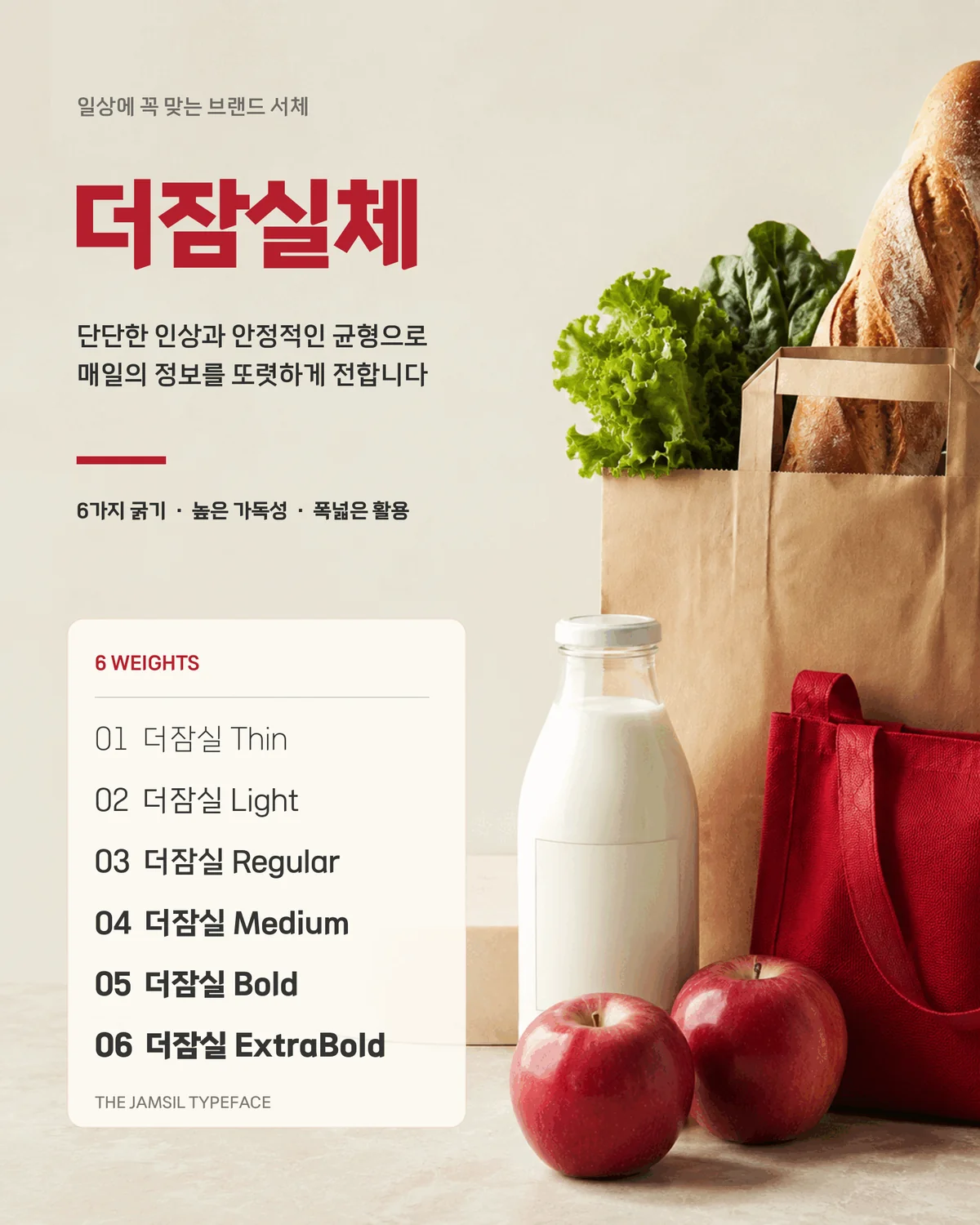
더잠실체 — 롯데쇼핑에서 배포하는 무료 폰트입니다. 누에고치와 명주실의 형태를 담아 단단함과 부드러움을 함께 표현한 고딕체
롯데쇼핑 롯데마트사업부가 폰트릭스와 함께 만들어 2023년 2월에 공개한 서체입니다. 총괄은 폰트릭스의 박용락 디자이너가 맡았고 개발에 열 달 남짓 걸렸습니다. 롯데마트의 신입 디자이너 열 명 남짓이 의견을 내 트렌드와 범용성을 검토했다는 점도 알려져 있습니다.
이름을 오해하기 쉬운데 롯데월드타워와는 관계가 없습니다. 잠실은 롯데의 출발점인 지역 이름이고, 한자로는 蠶室, 곧 누에를 치는 방이라는 뜻입니다. 모티브가 여기서 나옵니다. 제작사 설명 그대로, 누에가 뽕잎을 먹기 위해 머리를 드는 모습부터 누에고치를 만드는 과정, 마지막으로 누에고치에서 실을 뽑아내는 모습까지를 현대적으로 해석해 서체에 적용했습니다. 폰트릭스는 누에고치를 닮은 ㅇ꼴과 명주실의 생동감을 표현한 힘 있는 각을 특징으로 꼽습니다.
굵기는 여섯 가지로 이 목록에서 가장 촘촘한 축이고 베트남어와 인도네시아어까지 지원합니다. 라이선스에 한 가지 강한 조항이 있습니다. 인쇄와 출판, 영상, 웹, 모바일에는 자유롭게 쓸 수 있지만 서체를 수정하거나 다른 포맷으로 변형하는 것은 엄격하게 금지됩니다.
더잠실체는 롯데마트 브랜드 이미지와 잠실지역의 역사성을 함께 녹여낸 새로운 시도이며, 롯데의 헤리티지가 곧 잠실이라는 점에 주목하여 지역명 ‘잠실’을 서체의 이름으로 선정하였습니다. 국문, 영문 외 베트남 및 인도네시아어까지 개발하여 해외에서도 한글의 아름다움을 느끼고, 대한민국을 대표하는 지역으로서의 ‘잠실’을 알리는 것을 최종 목표로 하고있습니다… (발췌)